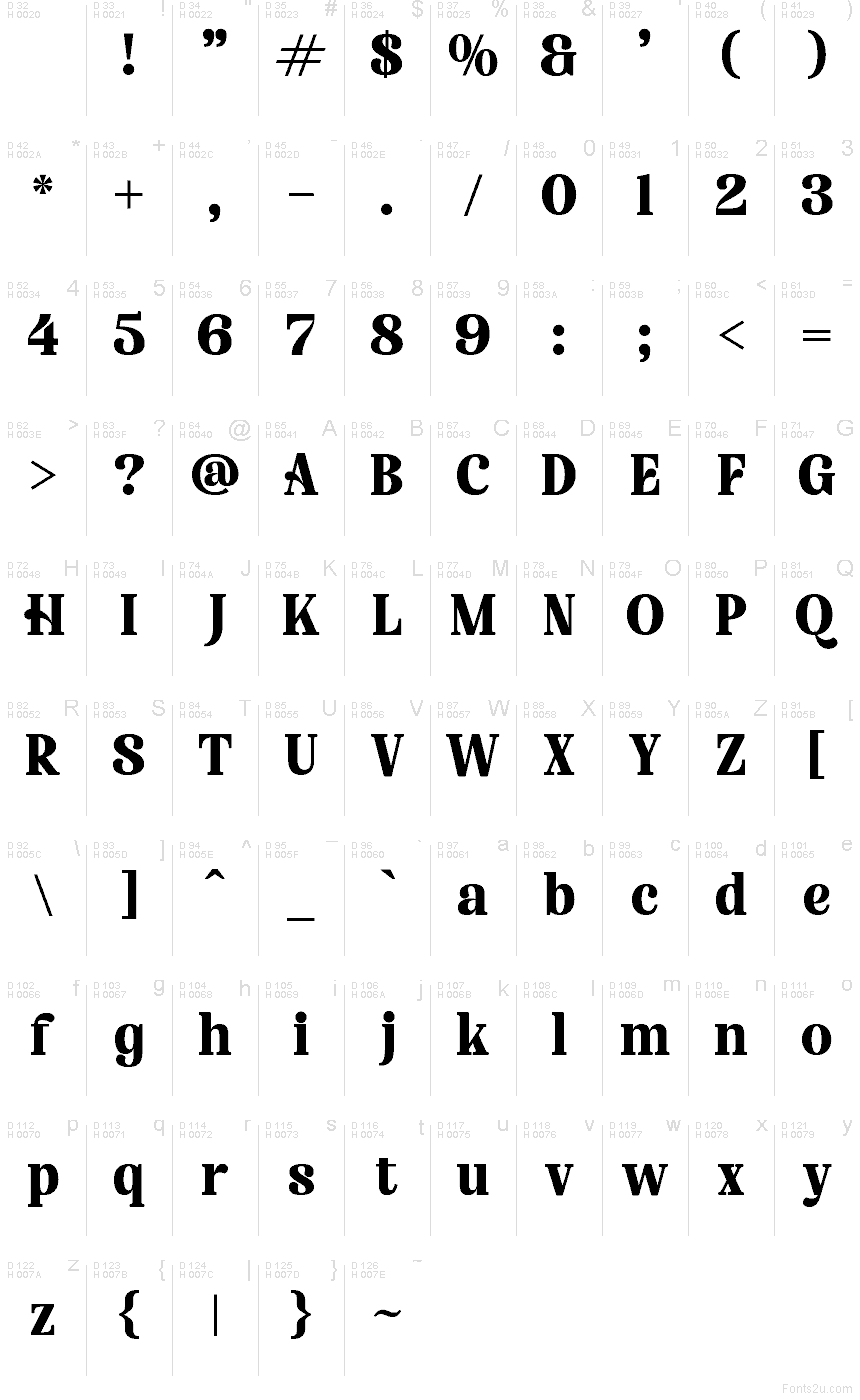
Nofiani Katrie par TimelessType.co est une police serif douce et gratuite, empreinte d'un caractère littéraire et légèrement romantique. Les lettres associent des empattements marqués à des courbes arrondies et généreuses, ce qui donne à cette police une allure formelle au premier regard, tout en restant accueillante et chaleureuse.
Elle convient parfaitement au branding, aux packagings de boutiques, aux titres de magazines, aux invitations et aux citations éditoriales où une police serif plus discrète peut faire la différence. En tant que police gratuite, elle est particulièrement efficace pour les titres courts et les logos, car ces courbes amples et ces empattements soignés confèrent une présence littéraire et composée, même à quelques lettres seulement.